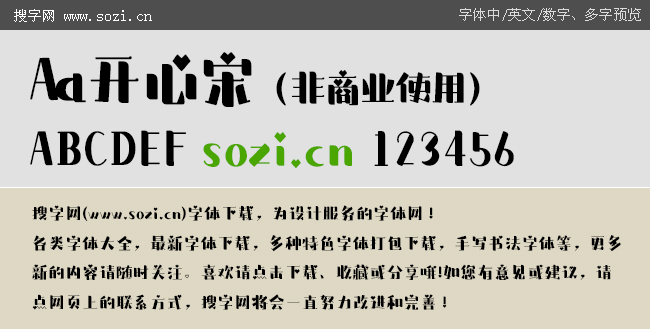
Aa開心宋
搜字網(wǎng)給大家提供一款A(yù)a開心宋(非商業(yè)使用)中文字體下載,Aa開心宋是一款藝術(shù)宋體字體,該字體筆觸粗實(shí)厚重,字形優(yōu)美,并裝飾有可愛的愛心圖案,非常有趣。適合應(yīng)用于藝術(shù)設(shè)計(jì)、平面宣傳設(shè)計(jì)、網(wǎng)頁設(shè)計(jì)、海報(bào)設(shè)計(jì)等應(yīng)用(此字體為個(gè)人非商用版,商用可以聯(lián)系QQ:1006760504)。